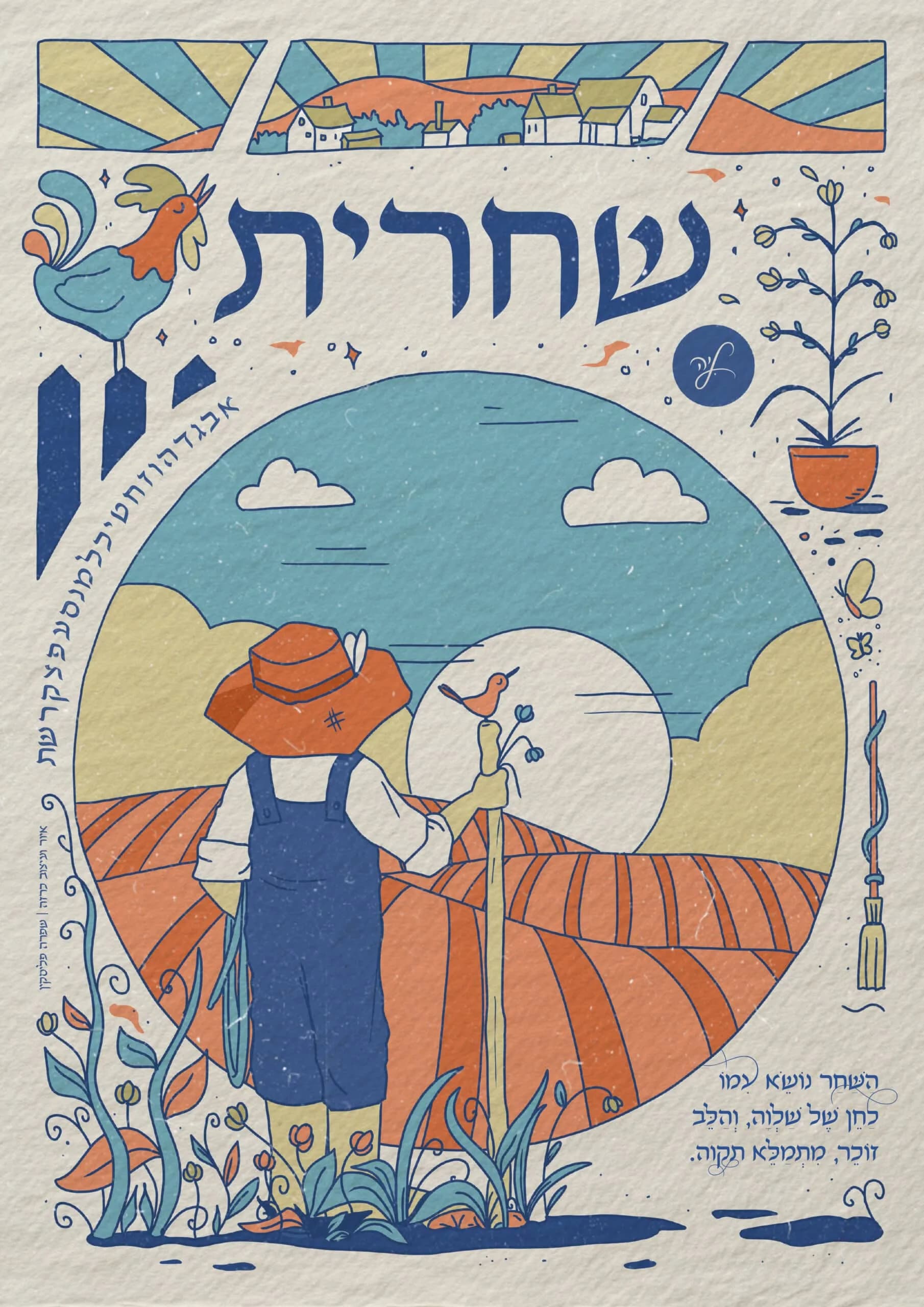
שחרית פונט "שחרית" – טיפוגרפיה אלגנטית של התחדשות והשראה "שחרית" הוא פונט עברי אלגנטי, המאופיין בקווים מעודנים, קישוטים קליגרפיים וטאץ' קלאסי. הפונט מבטא את תחושת ההתחדשות של הבוקר – את הרגע שבו האור מפציע ומביא איתו תקווה והתחלות חדשות. האותיות מעוצבות עם תנועה קליגרפית טבעית, המשלבות דיוק עם זרימה. שילוב של קווים עדינים עם עיטורים מסורתיים מעניק לכל טקסט מראה ייחודי. מתאים במיוחד לשימושים הדורשים אלגנטיות, רגש ומשמעות עמוקה. הפונט מושלם להזמנות לאירועים מיוחדים כמו חתונות, בר מצווה, בת מצווה ובריתות, לכתבי קודש, ברכות וטקסטים עם אופי מסורתי ורוחני. הוא אידיאלי גם לכותרות מרשימות ללוגואים, כרזות ודפוס יוקרתי, וכן לספרי שירה, סיפורים וכתבים המעוניינים לשדר הרמוניה ותחכום. פונט "שחרית" הוא בחירה מושלמת לכל מי שמחפש טיפוגרפיה שמספרת סיפור – מלאה בהשראה, עומק ואור. לחצו לאחר אות כדי לראות את האלטרנטיבה שלה | רישיון בחירת אפשרותדסקטופוובנקה כמות של פונט שחרית הוספה לסל עיצוב פוסטר: שפרה פליסקין